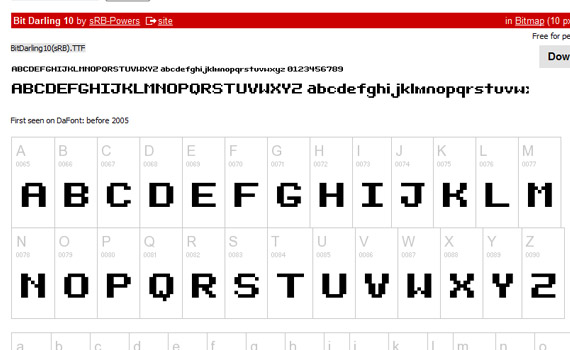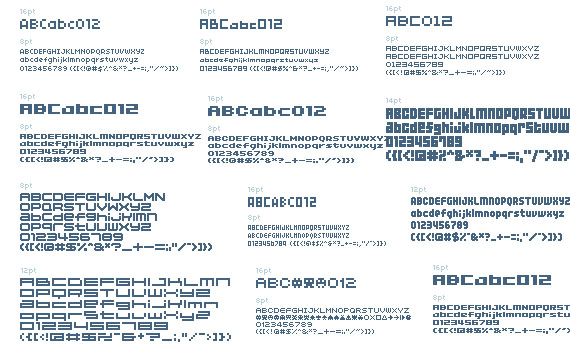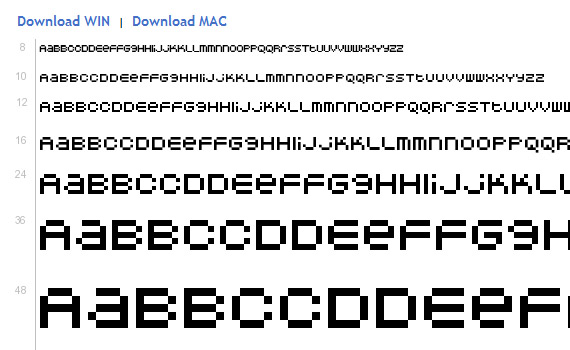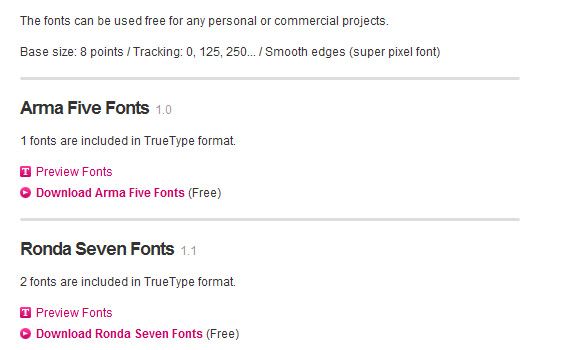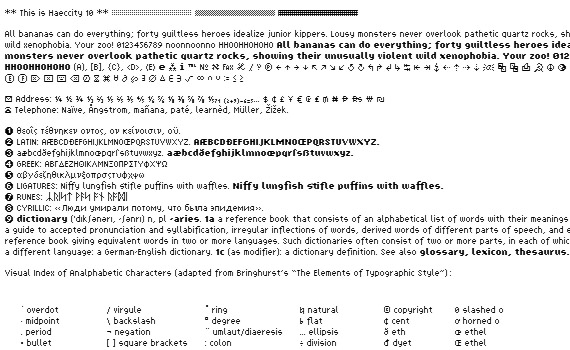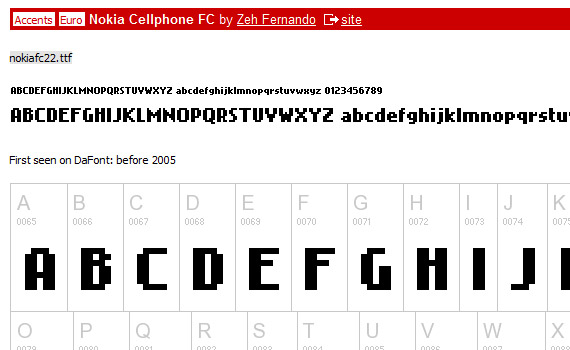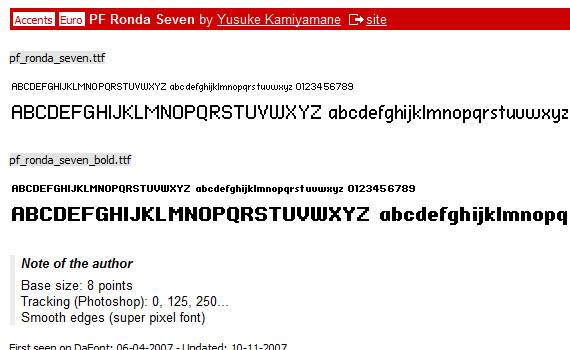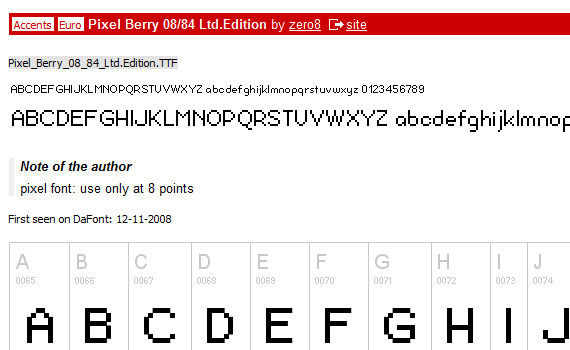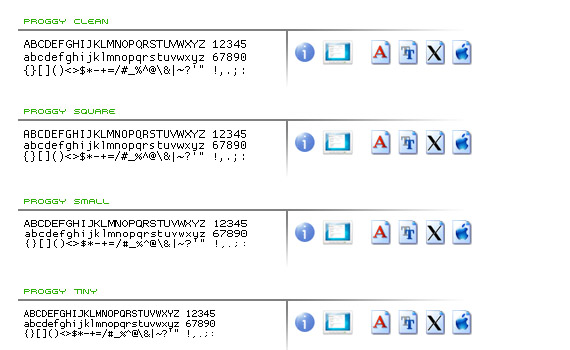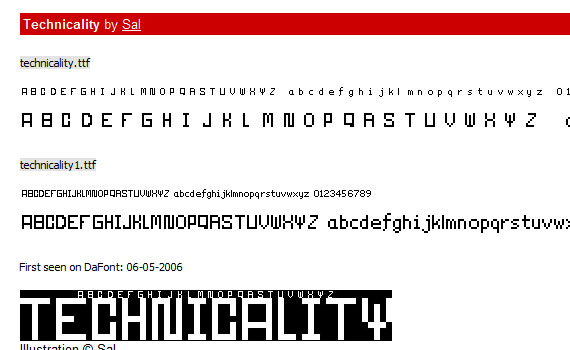
65个象素小号字体演示及下载
在网页设计中,很多位置都需要一些小又清晰的字体存在,像M4最常用的就是04字体,今天分享给大家的是65个小象素字体,非常实用。
1. Advocut
2. Technicality
3. Aux DotBitC
4. Pixel Berry
5. Pixelation
6. Visitor TT2 BRK
7. Bitdust Two
8. Bit Low
9. Bit Trip 7
10. Bit Light 10
11. Bit Cheese 10
12. Bit Darling 10
13. Bit Daylong 11
14. FFF Harmony
15. Apple
16. Pixel Mix
17. PF Tempesta Seven
18. Redensek
19. C&C Red Alert
20. Large 9
21. Wendy
22. Nokia Cellphone FC
23. PF Ronda Seven
24. Unborn Editrion
25. RuneScape UF
26. Acknowledge
27. Alterebro Pixel
28. Retro Rescued
29. Pixel Arial 11
30. Uni 05
31. 00 Starmap Truetype
32. Proggy Fonts
33. Free Fonts by Cal Henderson
34. Free Fonts by Yusuke Kamiyamane
35. Charriot
36. Victor’s Pixel Font
37. Haeccity
38. YoungDantes